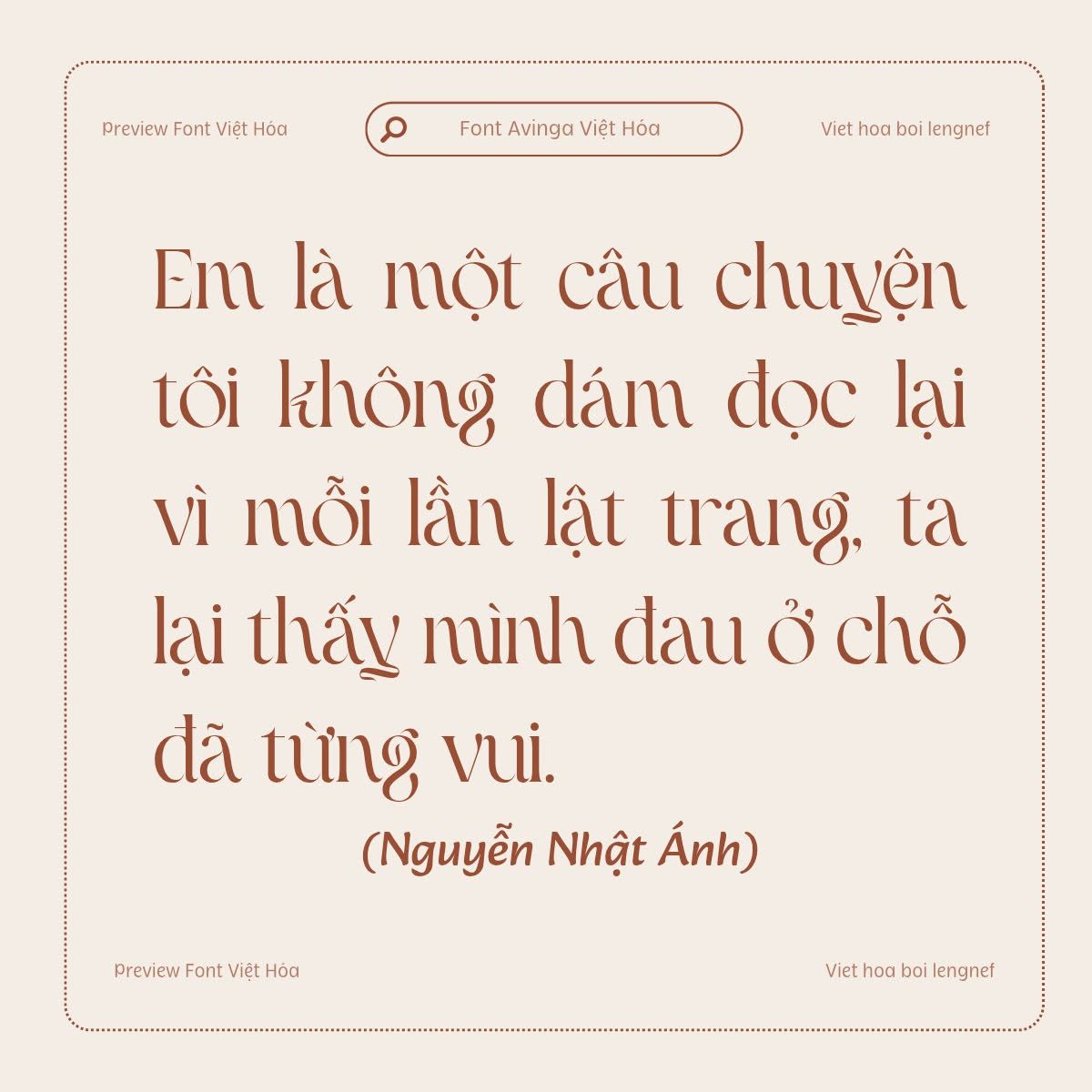
Share Font 76 || LF Avinga
- Tác giả: Zamroni Hamzah
- Việt hóa: lengnef
Phông chữ Avinga kết hợp sự thanh lịch điện ảnh với phong cách sang trọng, phù hợp với thiết kế logo và thương hiệu của bạn. Hoàn hảo cho những ai tìm kiếm sự tinh tế. Avinga đảm bảo thiết kế của bạn toát lên vẻ đẳng cấp và sang trọng.